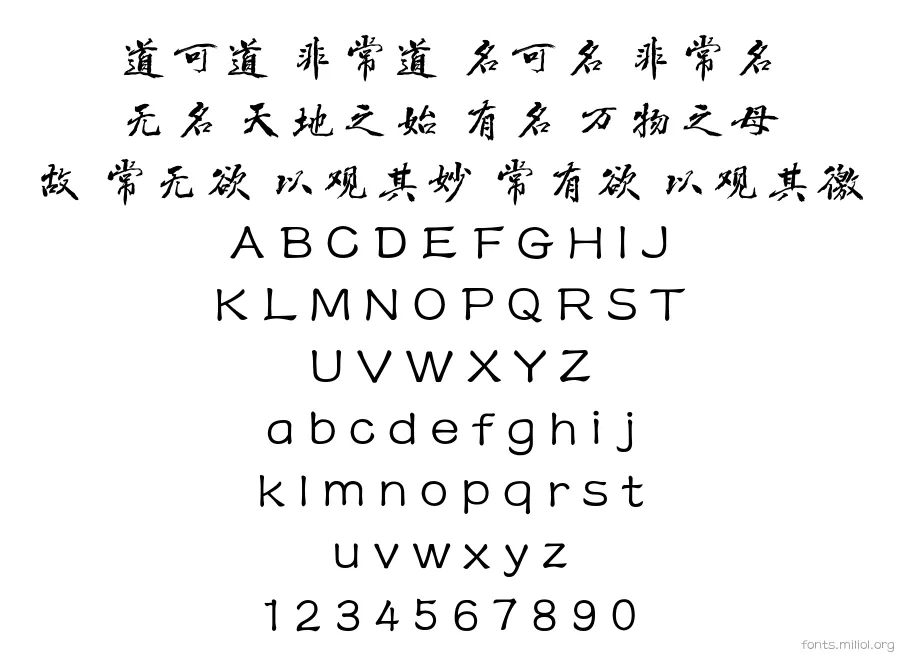
## 方正字迹-豪放行书简体:传统书法艺术的数字新生
方正字迹-豪放行书简体是一款融合传统书法精髓与现代设计美学的电脑字体。这款字体以行书为基础,保留了毛笔书写的自然韵律,笔画间流露出豪迈洒脱的气质,起承转合间尽显书法艺术的灵动之美。其简体设计在传承古典韵味的同时,更符合现代汉字规范,确保了良好的可读性。
在设计特点上,该字体笔势流畅连贯,横画略向右上倾斜,竖画挺拔有力,整体结构疏密得当。墨色浓淡的虚实变化通过数字技术得以呈现,使每个字符都仿佛跃然纸上。特别值得注意的是,连笔处的处理既遵循传统行书规则,又兼顾了屏幕显示的需求,在电子文档中也能展现出手写般的自然效果。
作为方正字库系列的重要成员,这款字体既适用于传统文化类设计项目,也能为现代商业设计增添独特的艺术气息。其兼容多种操作系统和设计软件的特性,让书法爱好者与设计师都能轻松调用这份数字化的书法瑰宝,在方寸屏幕间感受中华书法艺术的永恒魅力。